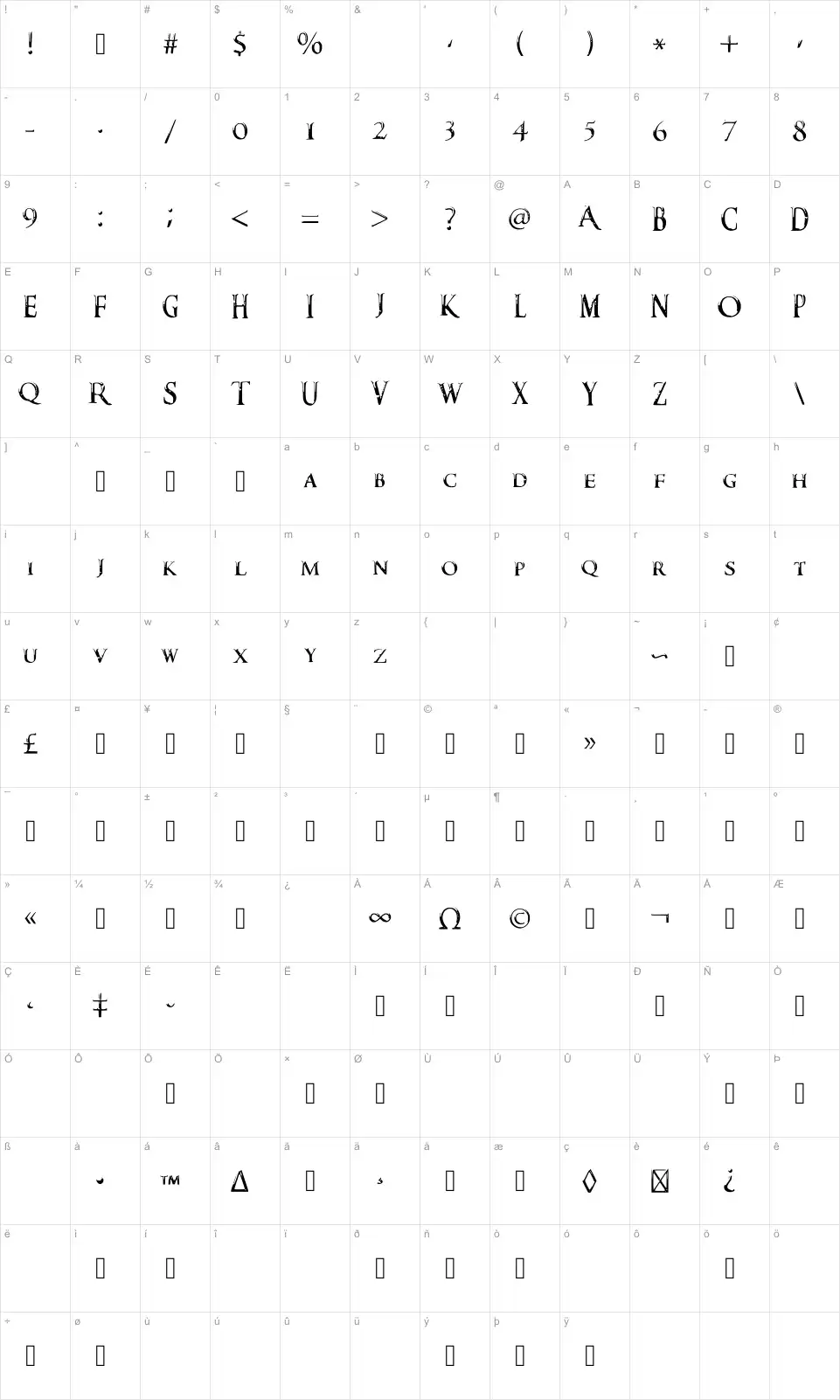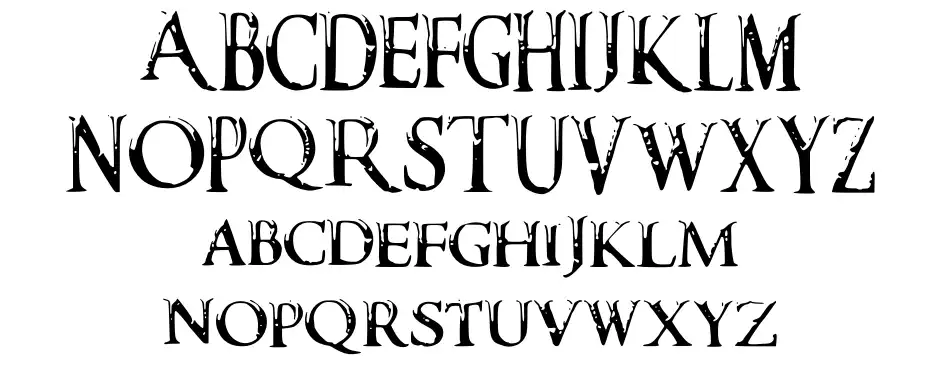
Darks Skyrim Font – Fonte Grátis
Darks Skyrim Font
A fonte Darks Skyrim Font, criada pelo designer DarkX ShadowX21, é uma escolha perfeita para quem busca um estilo gótico único e poderoso. Esta fonte pertence à categoria de Gothic e é uma excelente opção para personalizar designs de acordo com suas necessidades. Como uma fonte livre em formato TTF, ela é bastante versátil e permite que você use e personalize facilmente seus projetos. Adicionada em 12 de julho de 2022, a fonte já tem mais de quatro mil downloads, o que demonstra sua popularidade e qualidade. Com um tamanho de apenas 25 KB, é compacta o suficiente para ser facilmente baixada e utilizada em qualquer projeto. Se você está procurando por uma fonte que combine elegância com força, não há melhor escolha do que a Darks Skyrim Font. Experimente e descubra por si mesmo como ela pode se destacar em seus projetos.